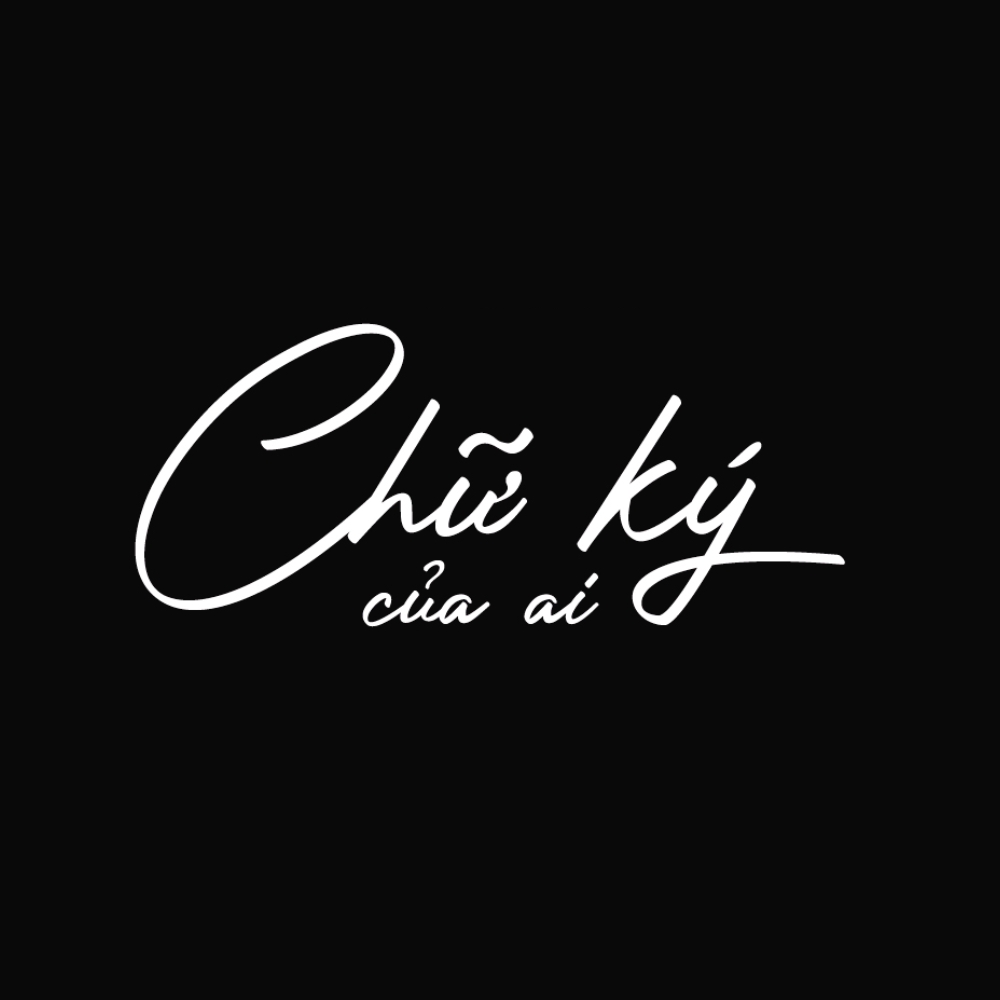
Font chữ ký Việt hóa là công cụ hỗ trợ đắc lực trong việc cá nhân hóa các bản thiết kế, mang lại cảm giác thủ công và sự gần gũi cho người xem. Khác với những kiểu chữ in ấn thông thường, dòng font này mô phỏng nét bút tay với độ mềm mại và nhịp điệu tự nhiên, thường được dùng để làm chữ ký email, thiết kế logo hoặc biển hiệu cho các không gian nghỉ dưỡng.
Đặc điểm nổi bật của các bộ font chữ ký Việt hóa
Dòng font này gây ấn tượng bởi cấu trúc nét vẽ bay bổng, mô phỏng sinh động kỹ thuật ký tên bằng bút mực hoặc bút lông. Điểm nổi bật của font chữ ký đẹp Việt hóa chính là khả năng tạo ra sự kết nối về mặt cảm xúc, giúp tiêu đề trở nên có hồn và tinh tế hơn. Việc Việt hóa chuẩn xác giúp các ký tự có dấu không bị lỗi hiển thị, duy trì sự liền mạch và tính thẩm mỹ cho toàn bộ nội dung văn bản.
Bên cạnh yếu tố thẩm mỹ, font chữ ký viết tay Việt hóa còn mang lại vẻ ngoài chuyên nghiệp và sự tin cậy cho cá nhân hoặc doanh nghiệp. Những nét uốn lượn được tinh chỉnh kỹ lưỡng giúp người thiết kế dễ dàng ứng dụng vào các phong cách kiến trúc hiện đại, tối giản hoặc phong cách vintage hoài cổ. Đây là lựa chọn linh hoạt để làm nổi bật tên thương hiệu homestay, quán cafe hoặc các lời nhắn gửi trong hồ sơ giới thiệu dự án.
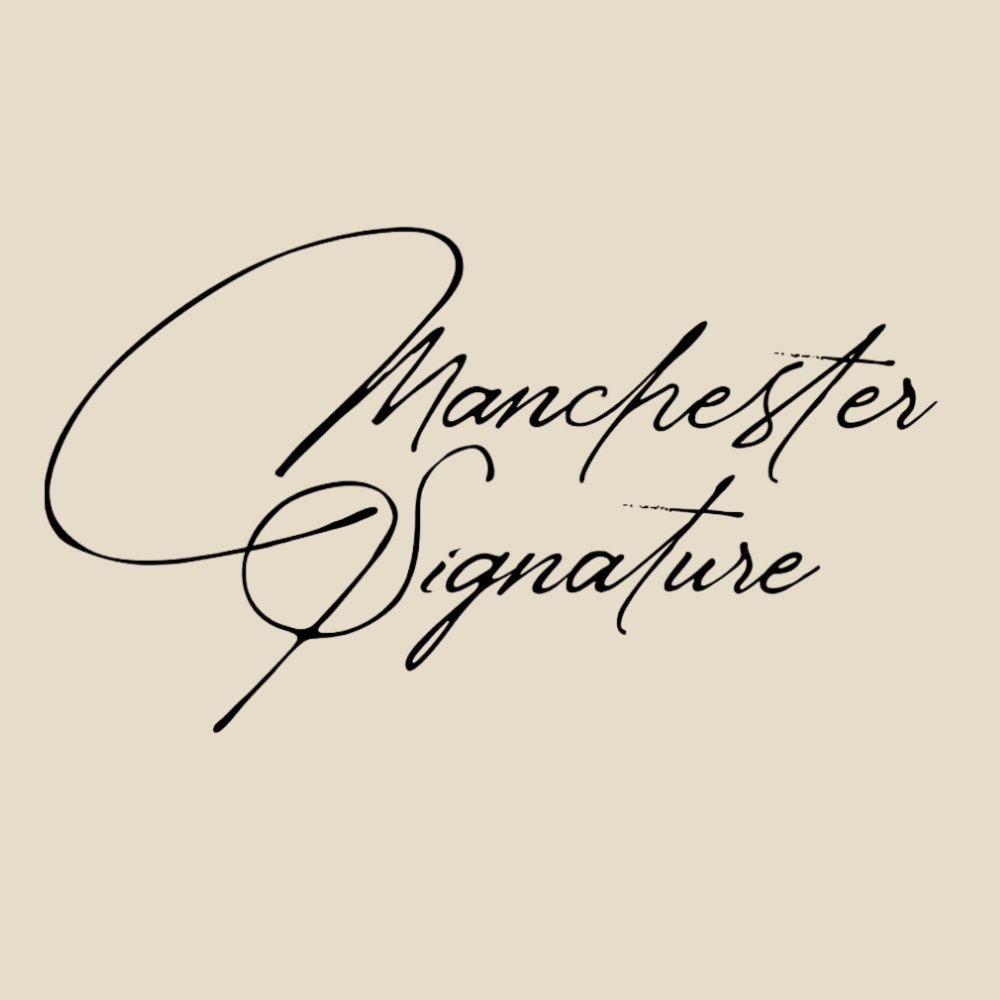
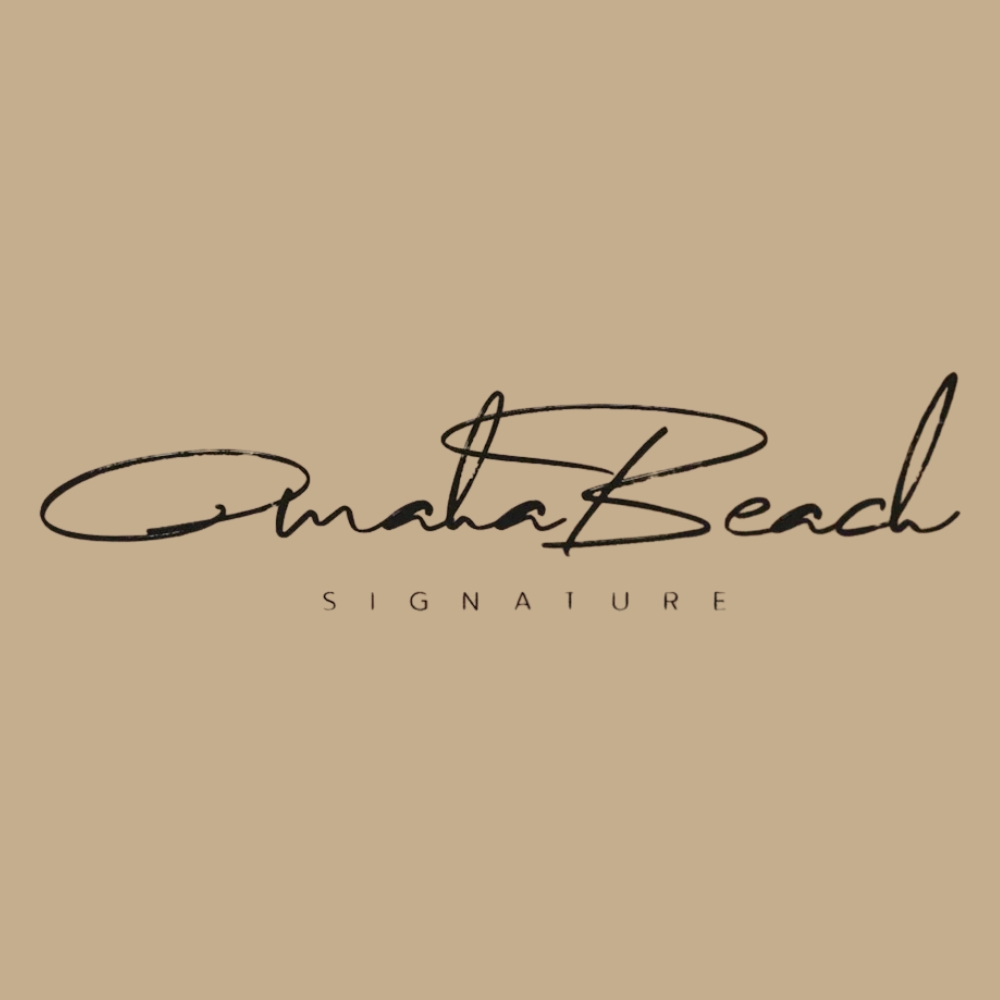
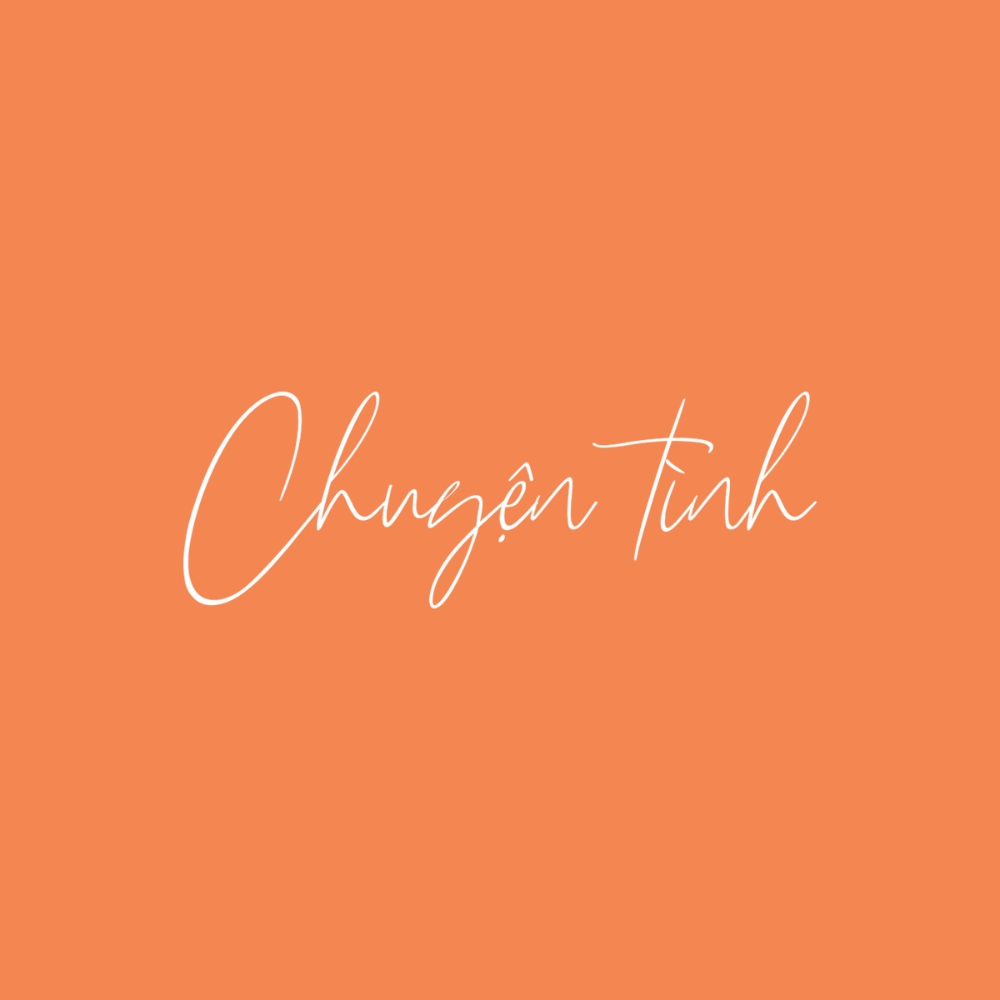
Gợi ý thiết kế: Font chữ ký thường có nét thanh mảnh và độ trang trí cao. Để đạt hiệu quả thị giác ổn định, bạn nên kết hợp chúng cùng các font không chân (Sans-serif) đơn giản cho phần nội dung chi tiết để tạo sự tương phản rõ rệt, giúp tiêu đề chính luôn nổi bật.
03 Ứng dụng font chữ ký đẹp Việt hóa vào đời sống
Nhờ vẻ ngoài giàu tính thẩm mỹ và cá tính, bộ font chữ này mang lại giá trị cao khi được đưa vào thực tế trang trí và quảng bá công trình:
- Bảng hiệu cho Homestay và Văn phòng: Những nét uốn lượn của font chữ ký rất ăn ý khi xuất hiện trên chất liệu gỗ hoặc mica gương. Đối với các dự án nhà lắp ghép nghỉ dưỡng, font chữ này giúp không gian trở nên thân thiện và có nét riêng biệt.
- Thiết kế bộ nhận diện cá nhân: Sử dụng font này để làm chữ ký email hoặc danh thiếp giúp bạn xây dựng hình ảnh chỉn chu và tạo ấn tượng tốt với đối tác trong các cuộc gặp gỡ, trao đổi công việc.
- Trang trí không gian nội thất: Bạn có thể dùng font chữ ký để cắt chữ nổi trang trí tại phòng khách hoặc khu vực sảnh chờ nhằm tạo điểm nhấn đầy nghệ thuật cho không gian sống hiện đại.
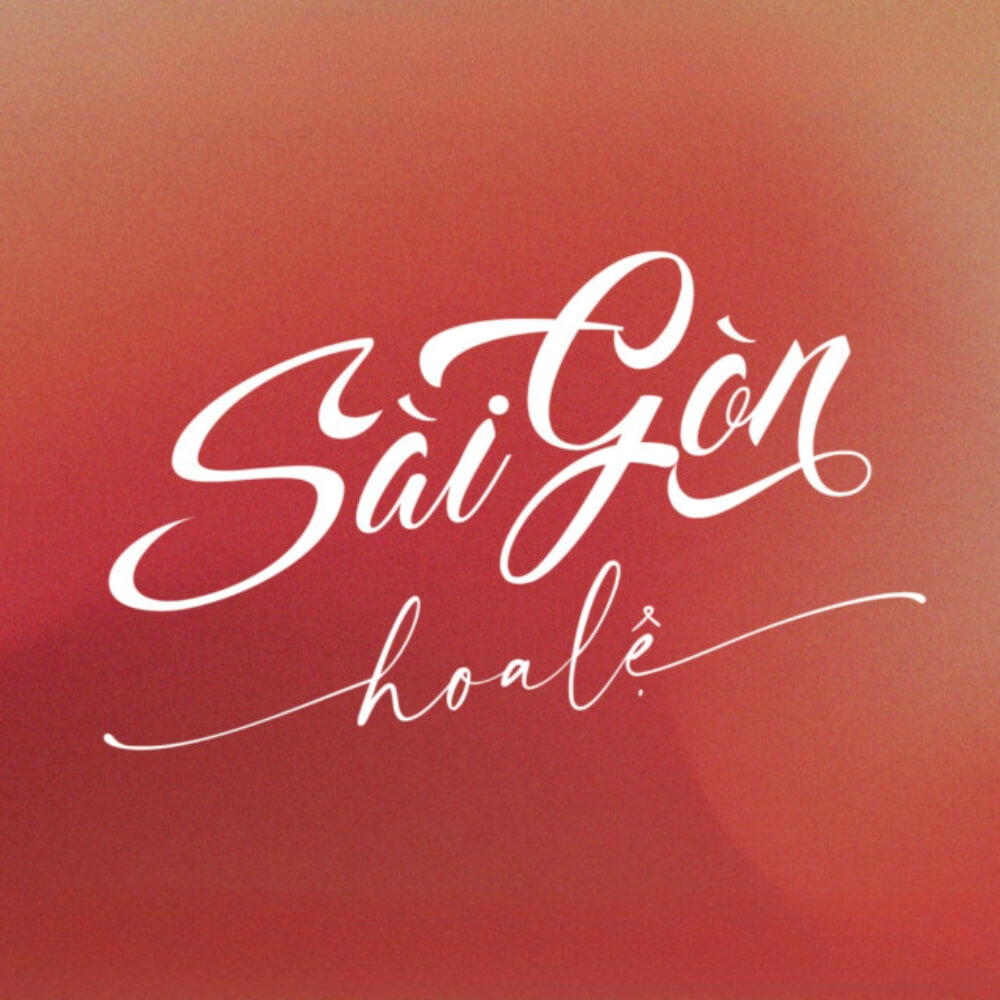
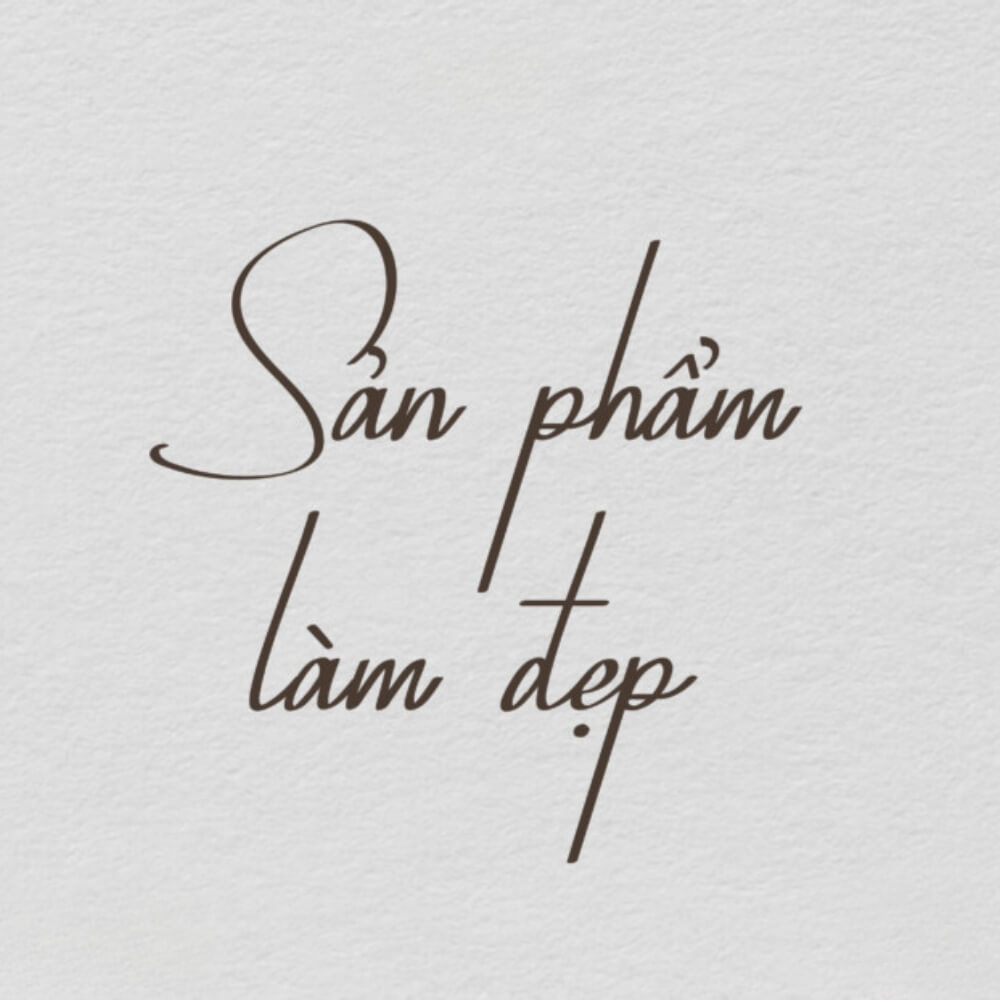
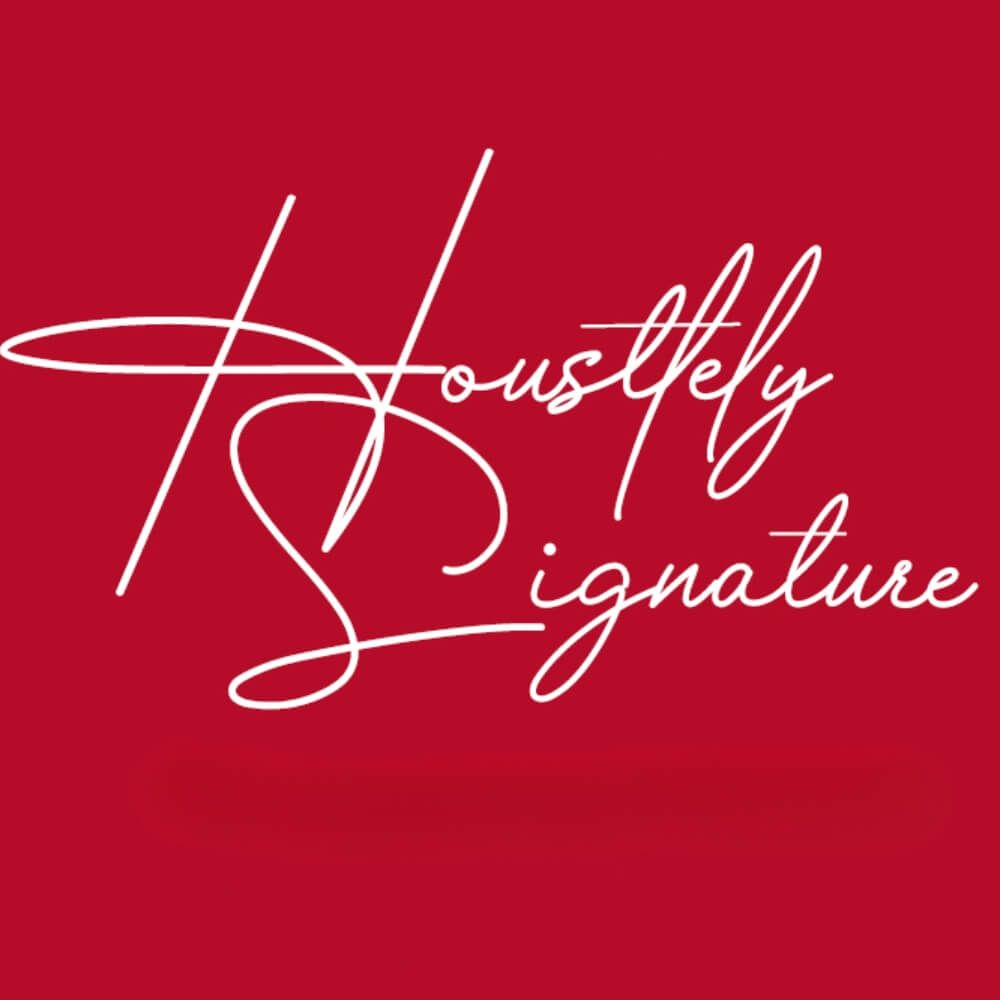
03 Lưu ý quan trọng khi thiết kế với font chữ ký viết tay Việt hóa
Để khai thác vẻ đẹp của các bộ font này một cách chuyên nghiệp, người thiết kế nên lưu tâm một số kinh nghiệm sau:
- Cân nhắc kích thước hiển thị: Do nét chữ mô phỏng chữ viết tay thường mảnh, bạn nên sử dụng ở kích thước đủ lớn để người nhìn dễ dàng nhận diện. Ở kích thước quá nhỏ, các nét uốn lượn có thể bị nhòe hoặc gây khó đọc.
- Hạn chế viết hoa toàn bộ: Đặc trưng của font script là các nét nối giữa chữ thường. Việc viết hoa toàn bộ cụm từ sẽ làm mất đi tính nhịp điệu tự nhiên và làm cho tiêu đề trở nên khô cứng, thiếu thẩm mỹ.
- Kiểm soát khoảng cách dòng: Một số font chữ ký có các nét móc vươn rộng ra xung quanh. Bạn cần nới rộng khoảng cách dòng để các nét không bị chồng lấn, giữ được sự thông thoáng cho bản thiết kế.